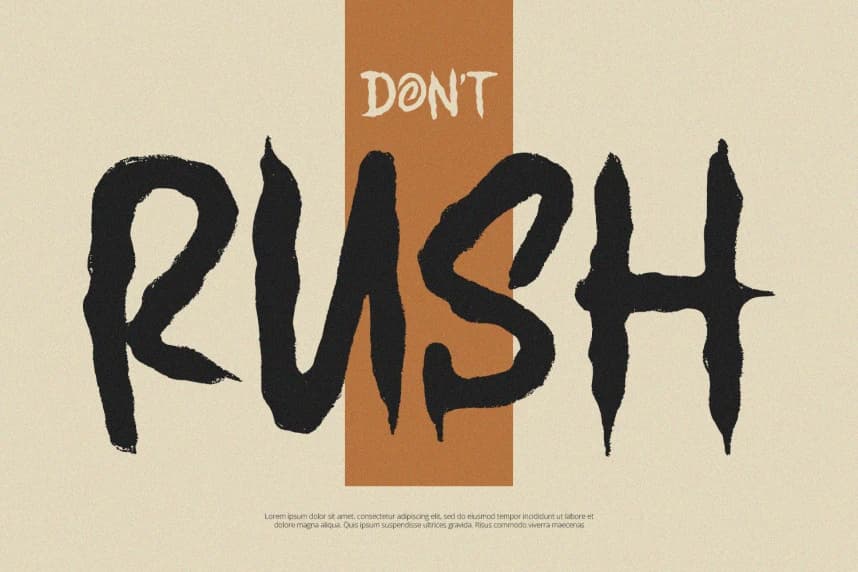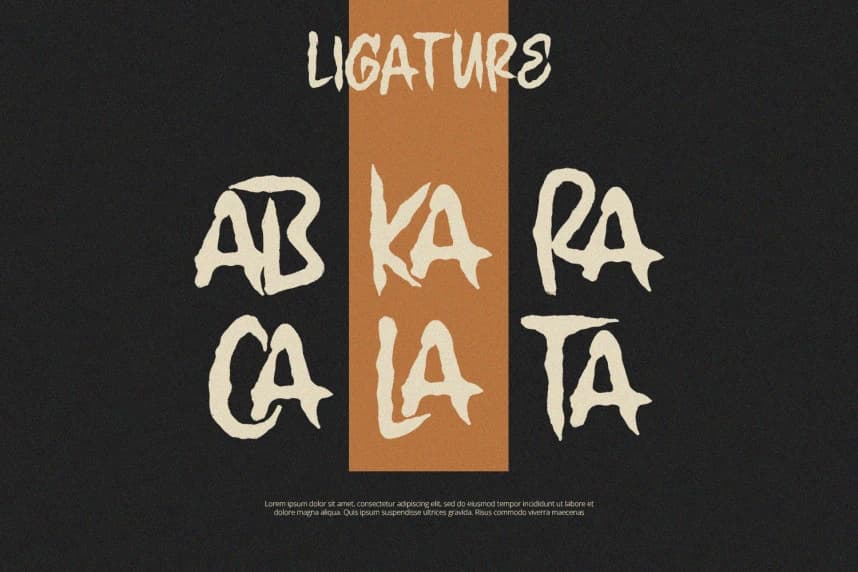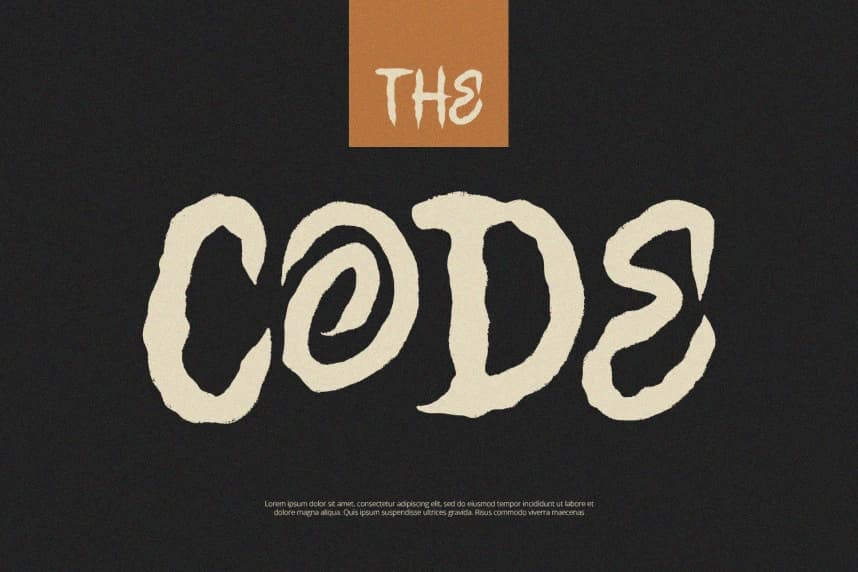
Grandore – Display Yazı Tipi
Grandore - Display Font, modern hissiyatlara sahip bir display fontudur. Branding, Logo Design, Lettering, Logotype, Clothing, Poster, magazine, packaging, posters, shopping bags, t-shirts, book covers, photography, special events ve diğer design projeleri için mükemmel şekilde kullanılacaktır.
Grandore – Display Yazı Tipi, modern bir hava taşıyan bir display yazı tipidir. Markalaşma, Logo Tasarımı, Lettering, Logotip, Giyim, Afiş, Dergi, Ambalaj, Posterler, Alışveriş Çantaları, Tişörtler, Kitap Kapakları, Fotoğrafçılık, Özel Etkinlikler ve diğer tasarım projeleri için mükemmel bir şekilde kullanılacaktır.